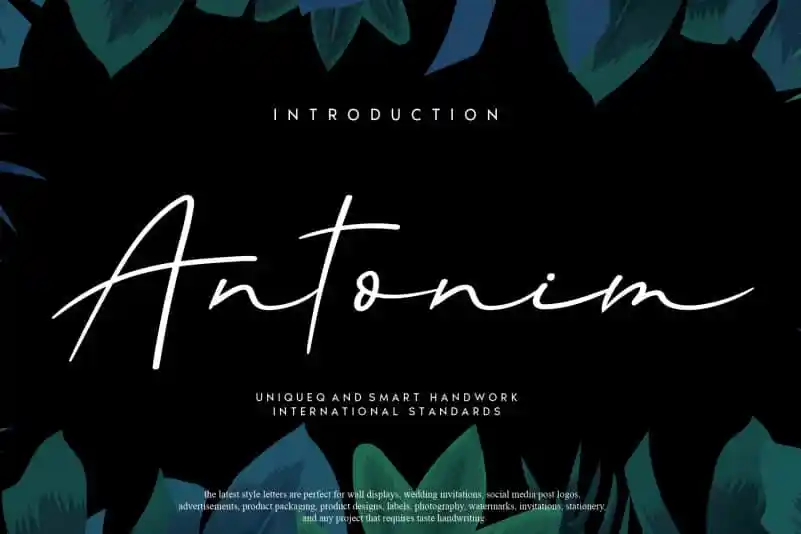
Antonim Script Font – Download Grátis
Na categoria de fãtes escritas, temos a Antonim Script Font que chega para enriquecer ainda mais seu trabalho gráfico com sua graça natural e personalidade única. Essa fonte é perfeita tanto para aqueles que buscam um estilo elegante e sofisticado quanto para aquelas ideias criativas que exigem algo mais peculiar. Seu design handwritten permite um toque autêntico e único à sua obra, tornando-a ainda mais especial. Criada pelo designer talentoso do andikastudio, a Antonim Script é uma opção perfeita para quem busca uma fonte de escrita manuscrita que se destaca. Com seu estilo elegante e detalhado, essa fonte oferece um toque profissional sem perder aquele charme único característico das fãtes escritas, tornando-a ideal tanto para criações digitais quanto para aplicação em impressões físicas. Seja no design de logotipos, editoriais ou até mesmo gráficos de marca – Antonim Script é uma escolha segura que certamente irá impressionar seus leitores e clientes com sua personalidade única e qualidade.